季節料理 五旬:四季を通じてお客様に心からの寛ぎとその折々の季節にあった食を味わってほしい。
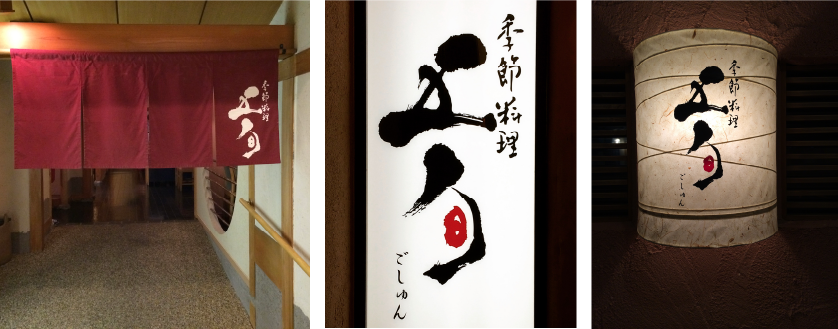
かすうどんチェーン「加寿屋」 狭山店舗外装/ツールデザイン
日本料理 笹川
株式会社一蔵 プロデュース店舗
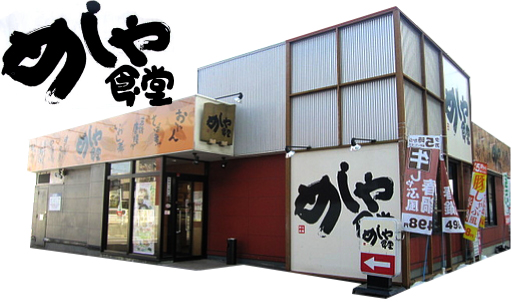
ろばた焼 伊豆島
神戸牛 嘉祥
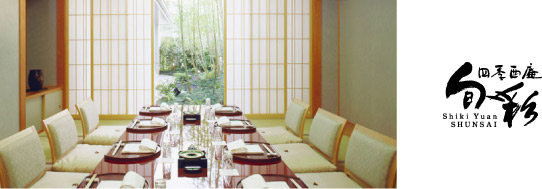
とまとの里 信濃路
どんぶり本舗
どんぶりの屋号を恵比須さんになぞらえ、背景に綴った文言も、円光に見たてて千客万来を願う、めでたいキャラクターに仕上げました。